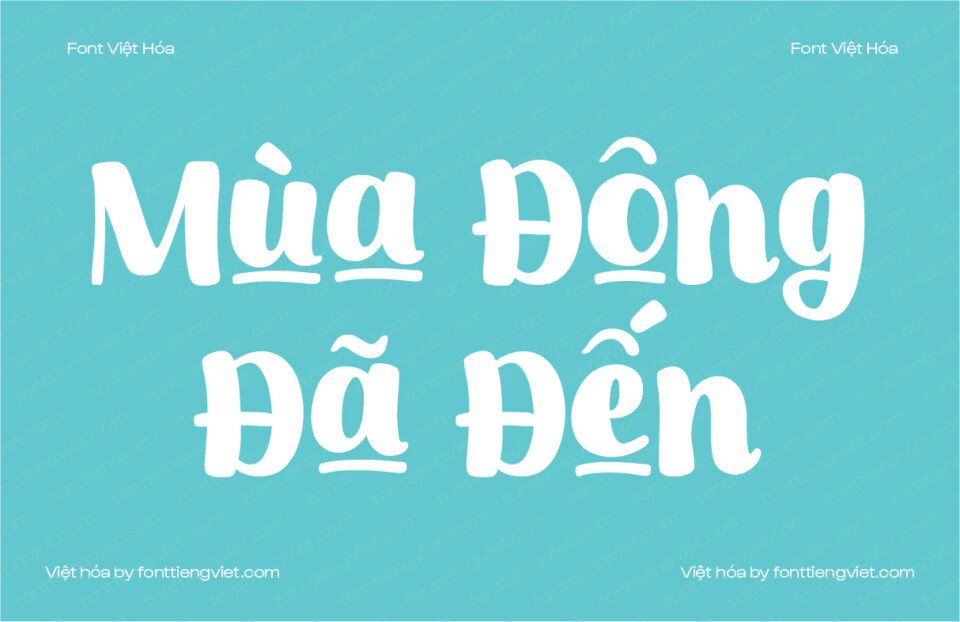
Font Việt hóa 1FTV Winter Half
Giới thiệu về Font Việt hóa 1FTV Winter Half
Trong thế giới thiết kế đồ họa, việc lựa chọn một Font Miễn Phí chất lượng luôn là ưu tiên hàng đầu của các bạn học sinh và thầy cô giáo. Font Việt hóa 1FTV Winter Half nổi lên như một lựa chọn hoàn hảo nhờ phong cách hiện đại, thanh lịch nhưng không kém phần ấm áp. Đây là bộ font được tinh chỉnh kỹ lưỡng để phù hợp với bảng mã tiếng Việt, giúp người dùng không còn lo lắng về lỗi hiển thị dấu khi soạn thảo văn bản hay làm slide thuyết trình.
Đặc điểm nổi bật của font chữ
Bộ Font Việt hóa 1FTV Winter Half sở hữu những đường nét thanh thoát, mô phỏng phong cách chữ viết tay mềm mại. Với cấu trúc chữ cân đối, bộ font này tạo nên cảm giác gần gũi, thân thiện, cực kỳ phù hợp cho các dự án thiết kế thiệp chúc mừng, bìa sách hoặc các bài giảng điện tử sinh động. Sự kết hợp giữa yếu tố cổ điển và nét vẽ tự do giúp tác phẩm của bạn trở nên độc đáo và thu hút ánh nhìn hơn bao giờ hết.
Ứng dụng Font Việt hóa 1FTV Winter Half trong giáo dục
Đối với môi trường học đường, Font Việt hóa 1FTV Winter Half là công cụ đắc lực giúp các em học sinh sáng tạo trong việc làm báo tường hoặc thiết kế poster sự kiện lớp. Các thầy cô có thể sử dụng font này để trang trí tiêu đề bài học, làm cho nội dung giảng dạy trở nên trực quan và thú vị hơn. Tính ứng dụng cao và khả năng hiển thị rõ nét trên cả màn hình lẫn bản in là điểm cộng lớn cho bộ font này.